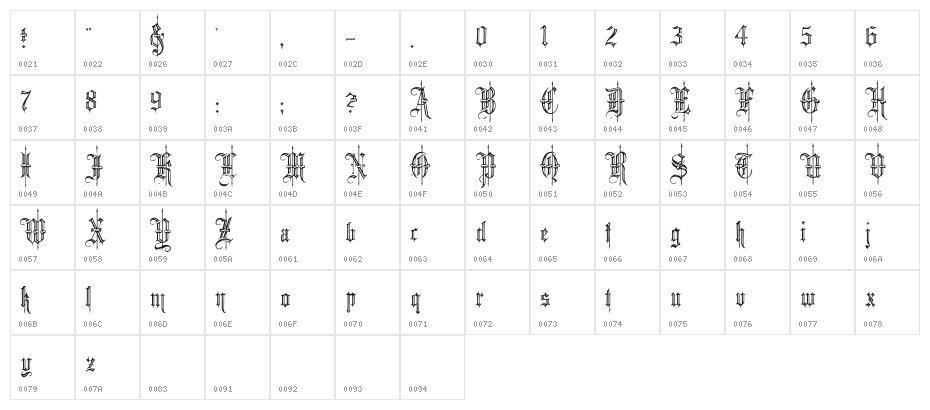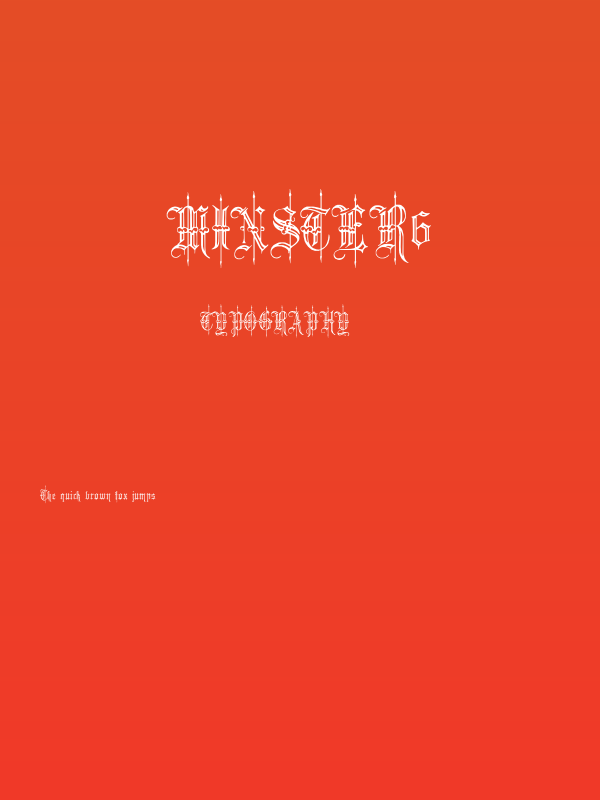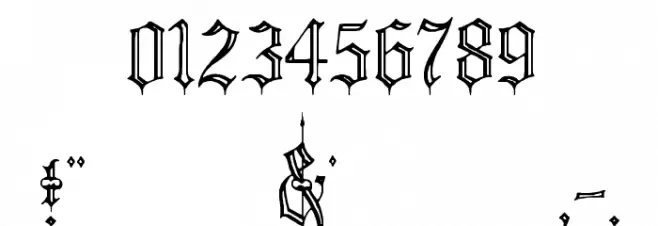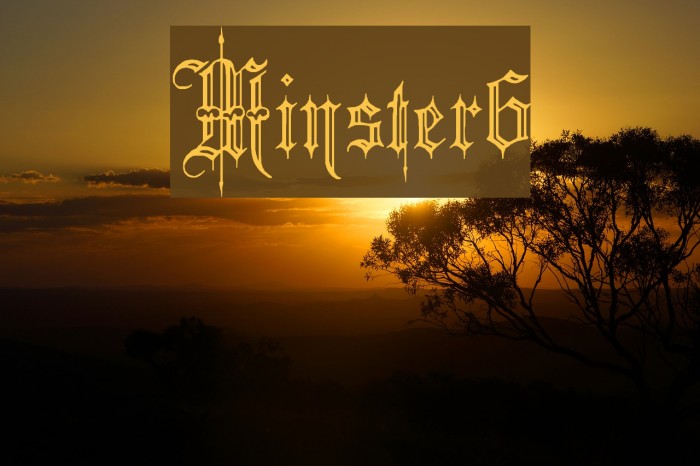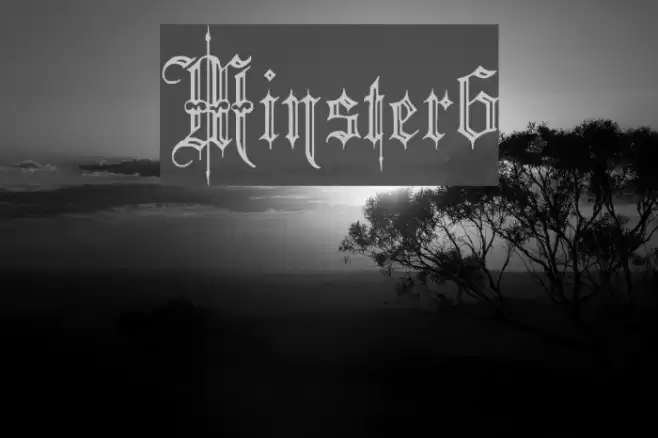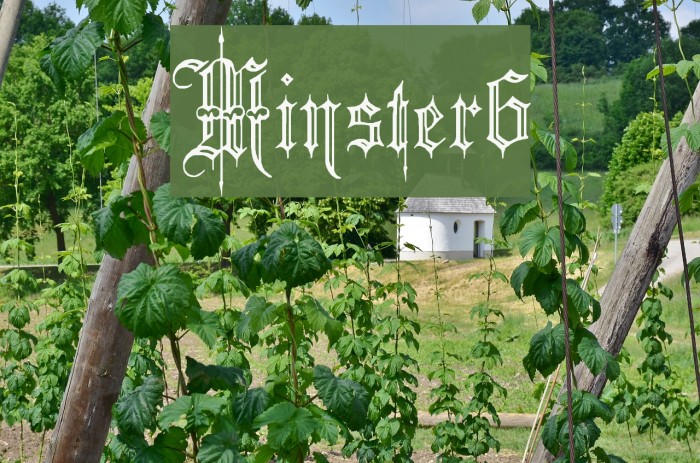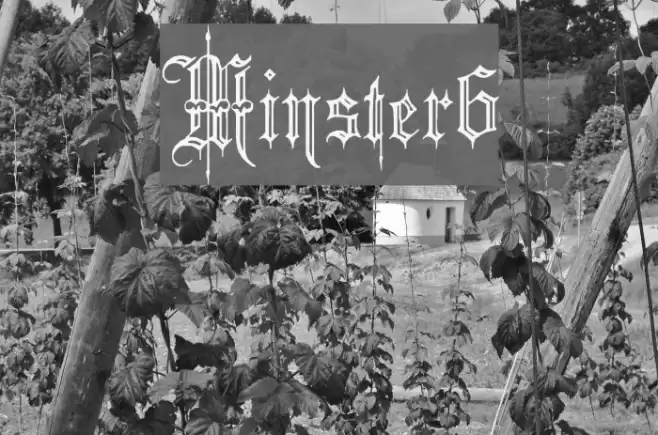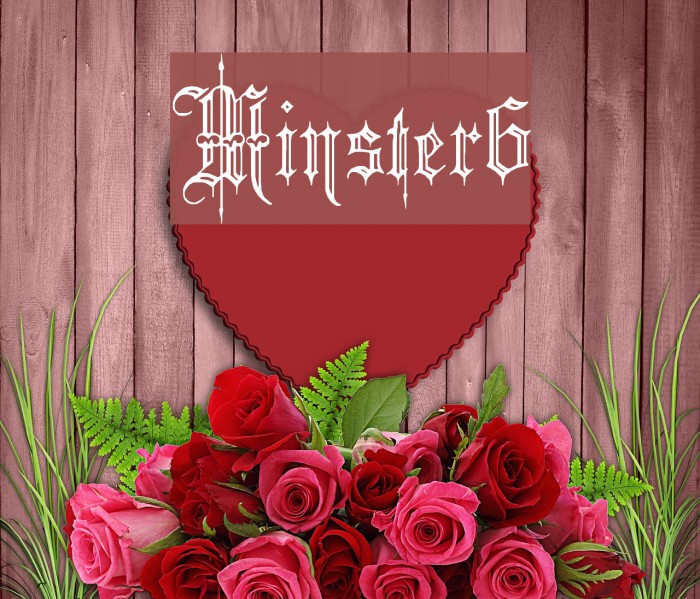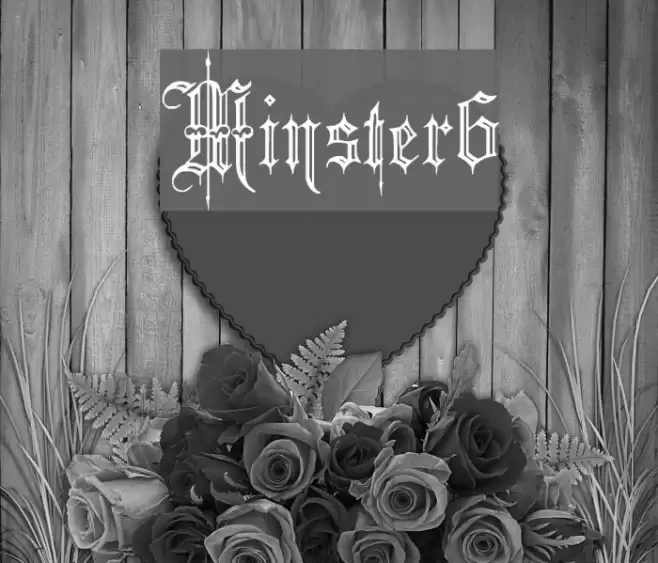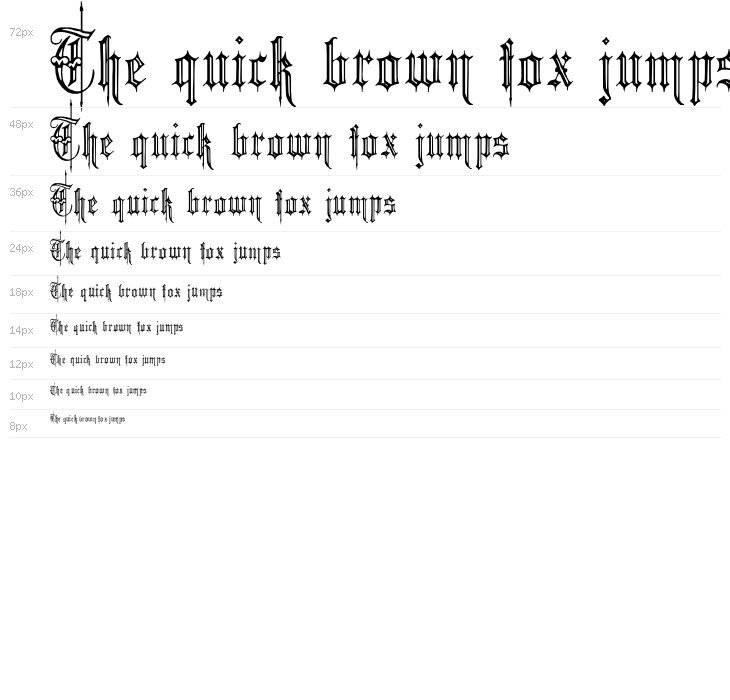
Minster6 Font
| Estilo general | Vintage |
| Caso de uso | Headlines, Logos, Decorative text |
| Proyectos propuestos | Suitable for wedding invitations, historical documents, gothic-themed designs, or branding that seeks a vintage or medieval aesthetic. |